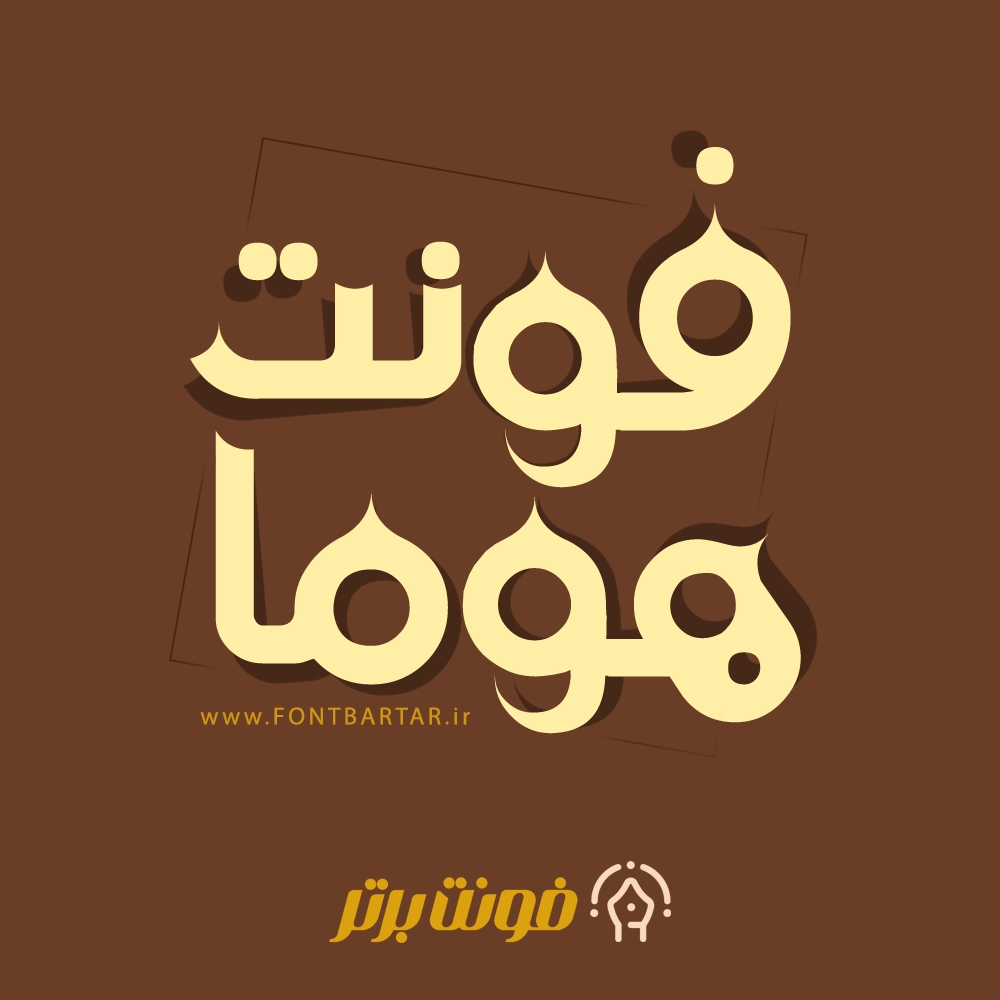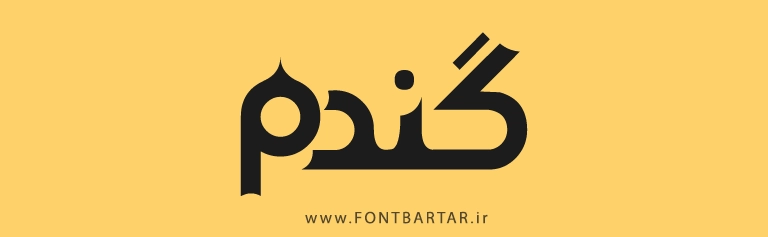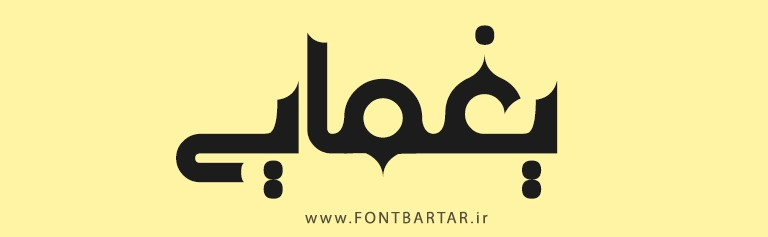
فونت جدید هوما
Homa Font
دانلود فونت جدید هوما – فونت جدید جذاب برای طراحی
فونت هوما یکی از فونت‌های خاص و متفاوت فارسی است که با طراحی منحصر‌به‌فرد خود، می‌تواند به پروژه‌های شما جلوه‌ای تازه و حرفه‌ای ببخشد. دانلود فونت جدید با الهام از سبک‌های مدرن و هندسی طراحی شده و در عین سادگی، حس خلاقیت و نوآوری را منتقل می‌کند.
اگر به دنبال یک فونت جدید برای طراحی پوستر، لوگو، تایپوگرافی یا حتی متن‌های وب‌سایت هستید، فونت هوما گزینه‌ای فوق‌العاده است. دانلود فونت جدید فارسی ترکیبی از زیبایی و خوانایی را در خود جای داده و می‌تواند در پروژه‌های گرافیکی و تبلیغاتی به کار رود.
ویژگی‌های فونت جذاب هوما:
• طراحی خاص و مدرن
• مناسب برای لوگوتایپ و تایپوگرافی
فونت لوگوتایپ هوما
فونت لوگو هوما
فونت هوما برای چه طراحی‌هایی مناسب است؟
فونت هوما برای طراحی لوگوتایپ، پوستر، بنر تبلیغاتی، تایپوگرافی و حتی متن‌های وب‌سایت مناسب است.